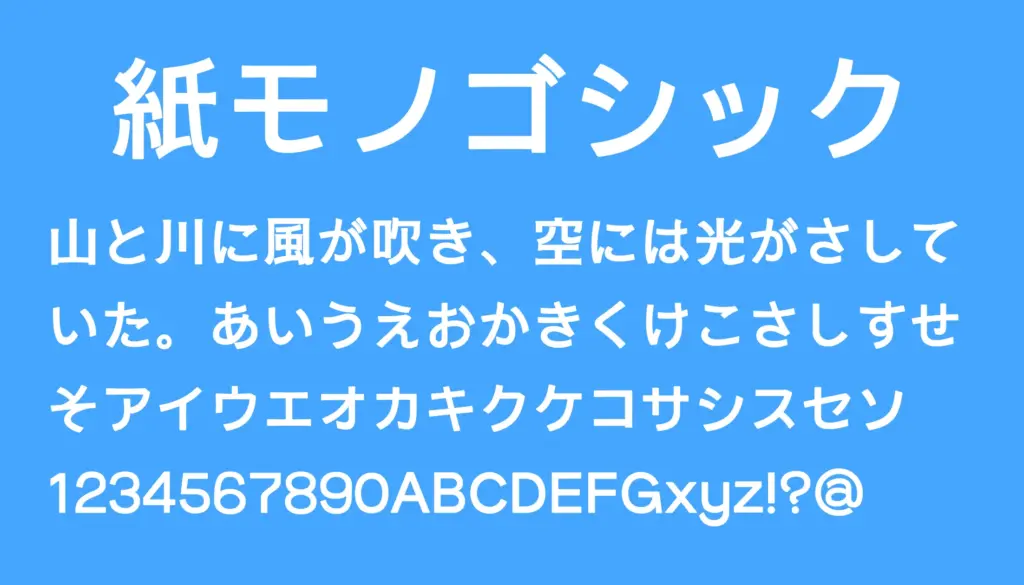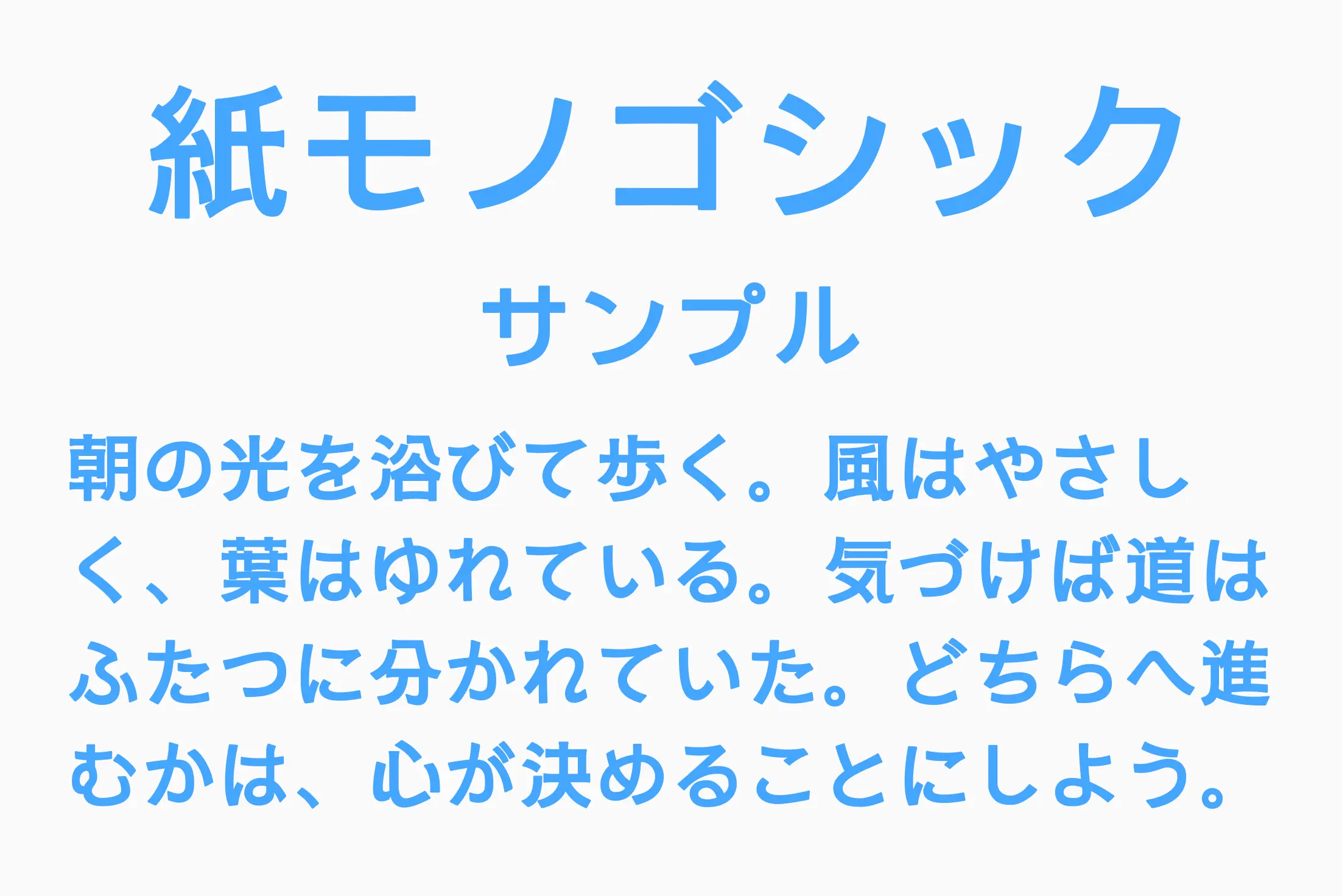
紙面向け見出し用に設計されたゴシック体フォント。モダンな字間(フトコロ)は広めながら、あえて洗練しすぎず、少し“野暮ったさ”を残すことで、親しみやすく“肉声感”のある温かな印象を実現しています。横画の両端や縦画のはじめに末広がりがあり、印刷物でもしっかり存在感を発揮。さらに、角丸と墨だまりの処理によって、柔らかく穏やかなデザインに仕上がっています
紙モノゴシック